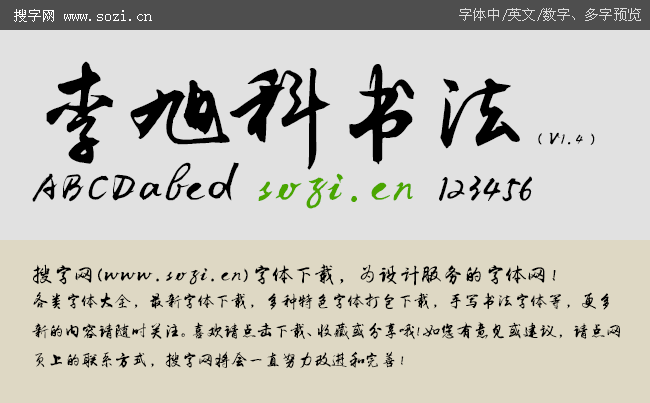
李旭科書法
搜字網(wǎng)提供一款李旭科書法字體下載,李旭科書法字體是一款手寫風(fēng)格的行書書法中文字體,該字體書寫流暢,瀟灑大方,整體效果十分出色。適合應(yīng)用于廣告設(shè)計(jì)、名片設(shè)計(jì)、包裝印刷、產(chǎn)品設(shè)計(jì)等應(yīng)用。